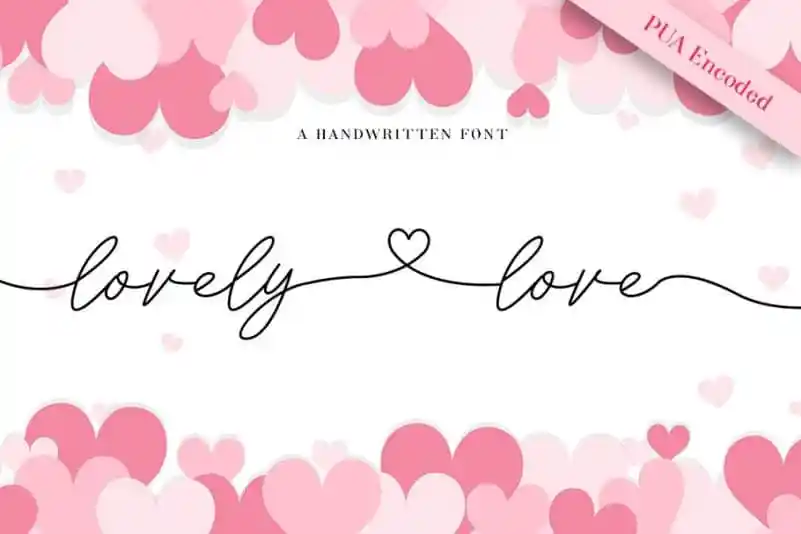
Lovely Love Handwritten Font – Download Grátis
A Lovely Love Handwritten Font é uma elegante tipografia script escrita à mão, perfeitamente adaptada para projetos variados do cotidiano até aqueles que requerem uma pegada mais sofisticada. Este tipo de texto moderno e descontraído pode ser facilmente utilizado tanto no título quanto na exibição de textos em corpo, oferecendo um estilo atraente e legível. A designer PuriCreative criou esta fonte com amor para que você possa inovar sua tipografia ao estilo do hand lettering moderno. Este tipo é especialmente adequado para uso junto com suas alternativas alternadas de caracteres, permitindo uma combinação perfeita em projetos profissionais e pessoais.